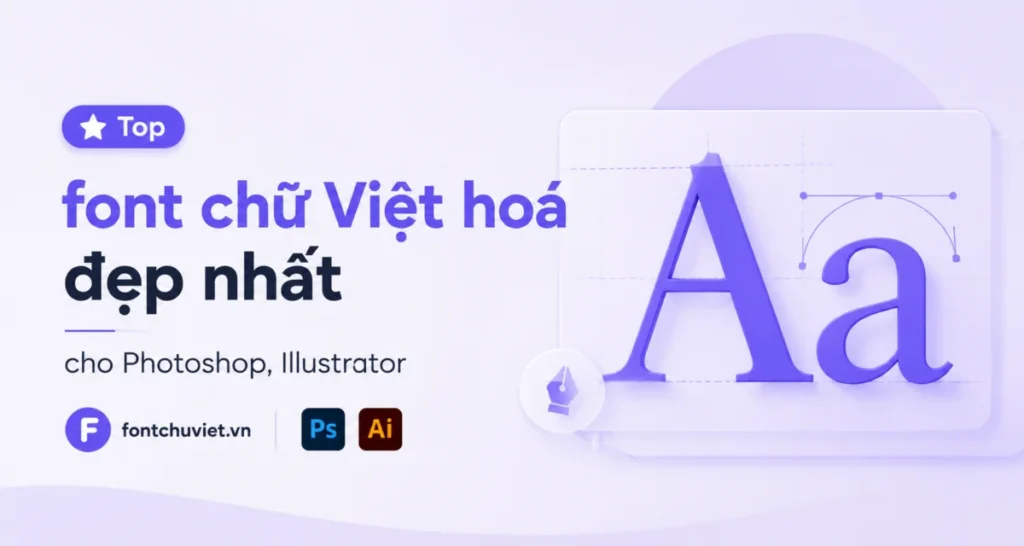
Top font chữ Việt hoá đẹp nhất cho Photoshop, Illustrator
Nếu bạn thường xuyên sử dụng Photoshop hoặc Illustrator để thiết kế banner, poster, thumbnail, logo hay typography thì việc sở hữu một bộ font chữ Việt hóa đẹp là điều gần như bắt buộc.
Một thiết kế đẹp không chỉ đến từ màu sắc hay bố cục mà còn phụ thuộc rất nhiều vào font chữ. Chọn đúng font có thể giúp thiết kế chuyên nghiệp hơn, dễ đọc hơn và truyền tải đúng cảm xúc của nội dung.
Trong bài viết này, chúng tôi sẽ tổng hợp top font chữ Việt hóa đẹp nhất cho Photoshop, Illustrator, đầy đủ dấu tiếng Việt, dễ sử dụng và phù hợp với nhiều phong cách thiết kế khác nhau.
Vì sao nên dùng font Việt hóa cho Photoshop, Illustrator?
Nhiều font quốc tế có thiết kế rất đẹp nhưng khi gõ tiếng Việt lại gặp lỗi như:
• Mất dấu tiếng Việt
• Dấu lệch, không cân đối
• Thiếu ký tự đặc biệt
• Chữ hiển thị thiếu chuyên nghiệp
Đây là lý do nhiều designer ưu tiên sử dụng font Việt hóa đầy đủ dấu để tránh mất thời gian xử lý lỗi.
Khi dùng font đã được Việt hóa tốt, bạn sẽ:
• Gõ tiếng Việt dễ dàng hơn
• Thiết kế đẹp và đồng bộ hơn
• Tiết kiệm thời gian chỉnh sửa
• Dễ dùng trong Photoshop, Illustrator, Canva hoặc Premiere
• Làm typography, banner, logo chuyên nghiệp hơn
Font chữ Việt hóa nào phù hợp cho Photoshop, Illustrator?
Không phải font nào đẹp cũng phù hợp với mọi thiết kế.
Mỗi nhóm font thường có thế mạnh riêng.
Font sans serif – hiện đại, dễ đọc
Đây là nhóm font không chân rất phổ biến trong thiết kế hiện đại.
Phù hợp cho:
• Banner quảng cáo
• Thumbnail YouTube
• Thiết kế social media
• Website
• Poster công nghệ
• Typography hiện đại
Ưu điểm lớn nhất là sạch sẽ, dễ đọc và phối layout dễ.
Font serif – sang trọng, cao cấp
Nếu làm các thiết kế thiên về:
• Mỹ phẩm
• Nhà hàng
• Luxury branding
• Thiệp cưới
• Bao bì cao cấp
thì font serif Việt hóa thường mang lại cảm giác tinh tế và chuyên nghiệp hơn.
Font handwritten – viết tay nghệ thuật
Đây là nhóm font giúp thiết kế có cảm xúc hơn.
Rất phù hợp với:
• Typography quote
• Poster cảm xúc
• Thiệp
• Menu cafe
• Thiết kế nữ tính
• Branding handmade
Tuy nhiên không nên dùng cho đoạn văn dài vì sẽ khó đọc.
Font display – nổi bật cho tiêu đề
Nếu bạn làm banner sale, poster hoặc thumbnail, đây là nhóm font rất nên có.
Ưu điểm:
• Thu hút ánh nhìn
• Dễ tạo điểm nhấn
• Hợp làm headline lớn
Một tiêu đề đẹp thường quyết định cảm giác của cả thiết kế.
Cách chọn font đẹp cho Photoshop và Illustrator
Designer mới thường mắc lỗi chọn font theo cảm tính.
Thực tế, nên chọn font theo mục tiêu thiết kế.
Ví dụ:
Banner khuyến mãi → font đậm, rõ, dễ đọc.
Logo thương hiệu cao cấp → serif hoặc sans serif thanh lịch.
Poster typography → kết hợp font display + font nội dung.
Thumbnail video → ưu tiên font đậm, nổi bật, dễ nhìn từ xa.
Một nguyên tắc rất dễ nhớ:
Thiết kế càng nhiều chữ → càng ưu tiên dễ đọc.
Thiết kế càng ít chữ → càng có thể sáng tạo với font.
Designer có nên cài quá nhiều font?
Nhiều người cài vài nghìn font khiến Photoshop hoặc Illustrator load chậm, khó tìm đúng font khi làm việc.
Thay vì vậy, hãy xây dựng một bộ font riêng gồm:
• Font tiêu đề
• Font nội dung
• Font branding
• Font social media
• Font viết tay
• Font vintage
• Font hiện đại
Khi cần thiết kế, bạn sẽ làm việc nhanh hơn rất nhiều.
Top font chữ Việt hóa đẹp cho Photoshop, Illustrator
Dưới đây là danh sách các font chữ Việt hóa đẹp nhất cho Photoshop và Illustrator, đầy đủ dấu tiếng Việt, dễ dùng và phù hợp cho nhiều nhu cầu thiết kế từ banner, poster, logo đến typography.
Font VL Andalusia – Font Việt hoá
Font VL Amtenar – Font Việt hoá
2 Font VL Ample – Font Việt hoá
Font VL Amelia BT – Font Việt Hoá
Kết luận
Một bộ font chữ Việt hóa đẹp không chỉ giúp thiết kế đẹp hơn mà còn tăng tốc quá trình làm việc trong Photoshop và Illustrator.
Nếu thường xuyên làm banner, poster, logo, typography hoặc social media, việc sở hữu những font Việt hóa chất lượng là điều rất đáng đầu tư.